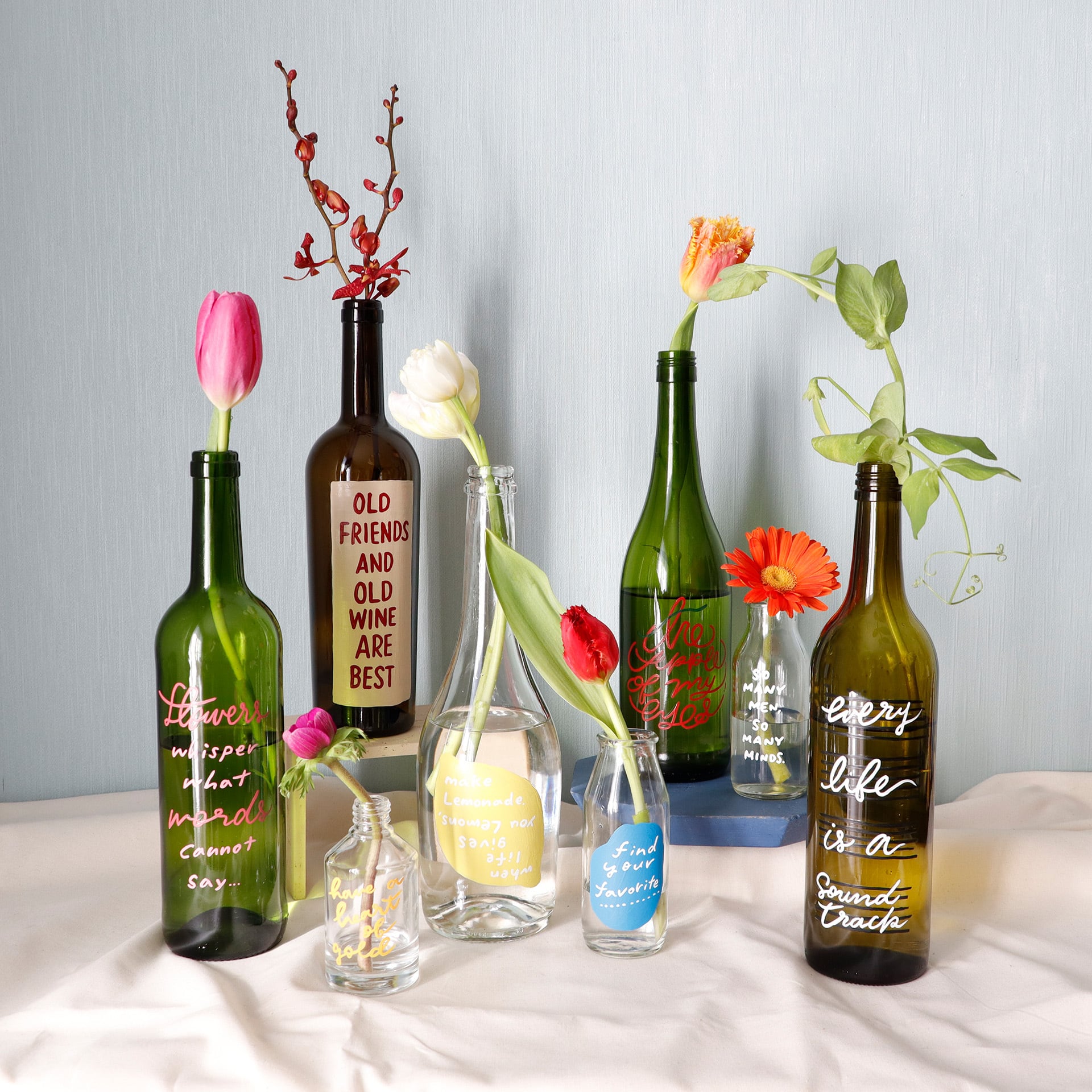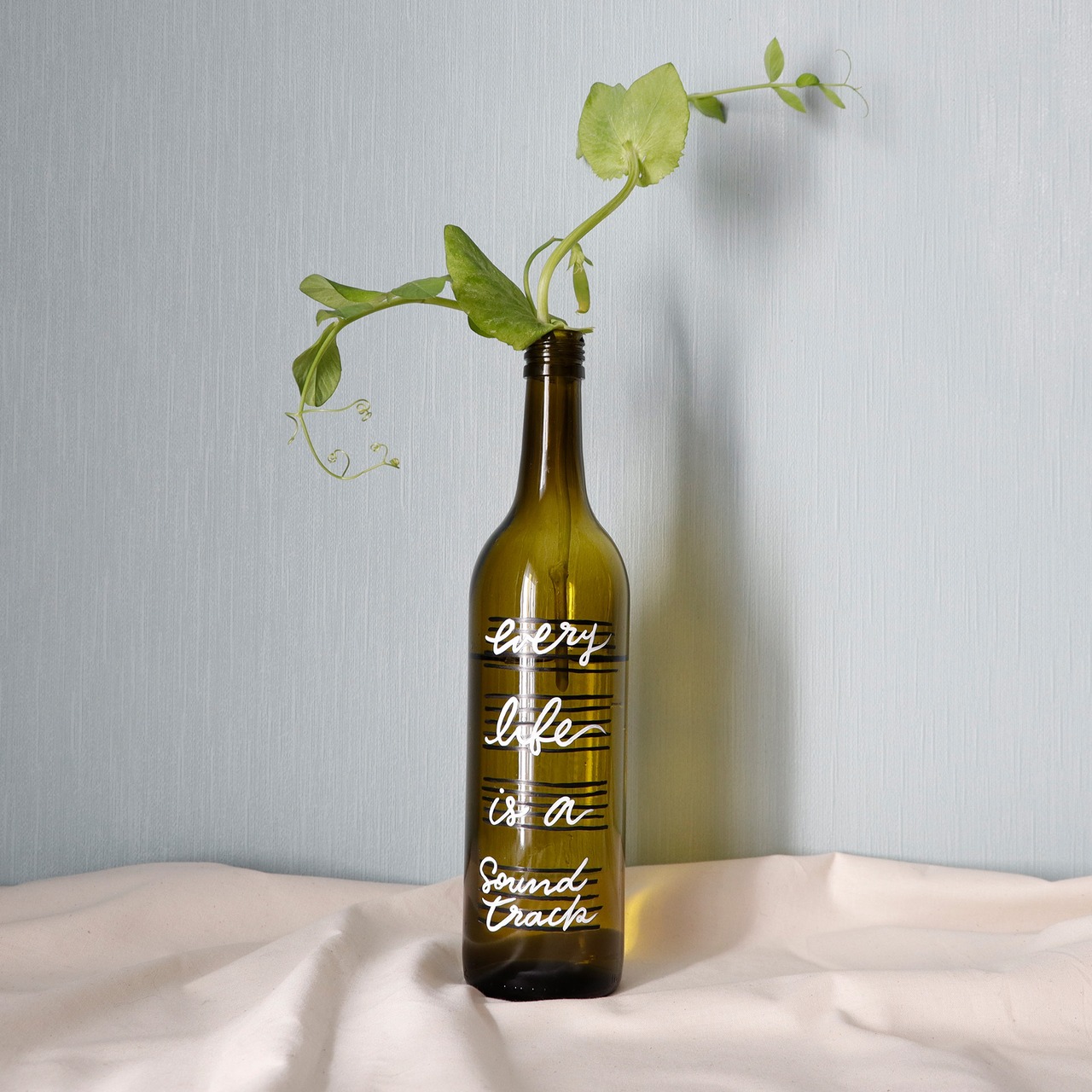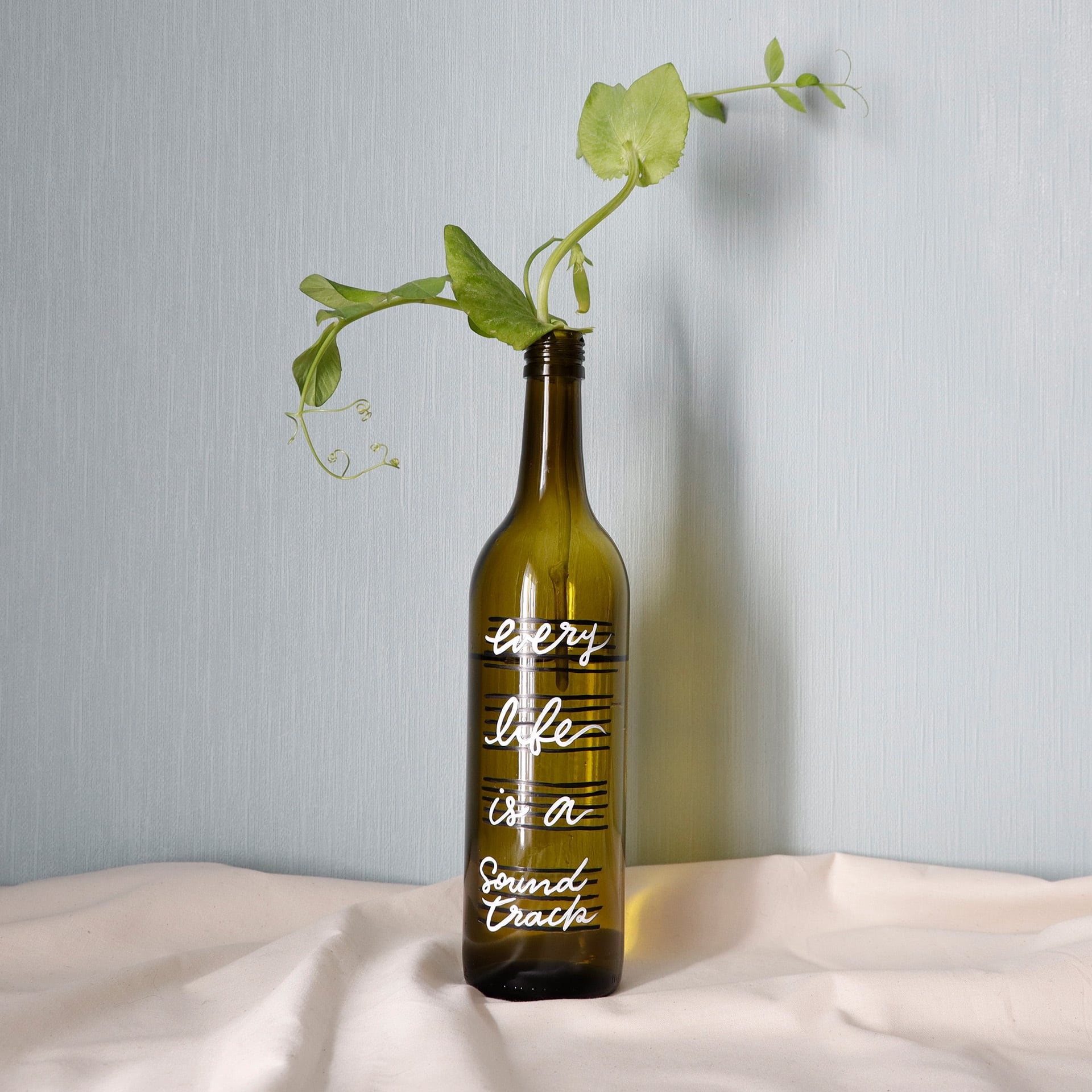
【BOTTLE PAINT ART】every life has a soundtrack
every life has a soundtrack
全ての人生にはサウンドトラックがある
五線譜に文字が乗っています♪
楽譜っぽく、白と黒で描いてるのでグリーンなお花が似合うかも?
光が入るとこに置くと、瓶の色とともに文字も影になって素敵ですよ!!